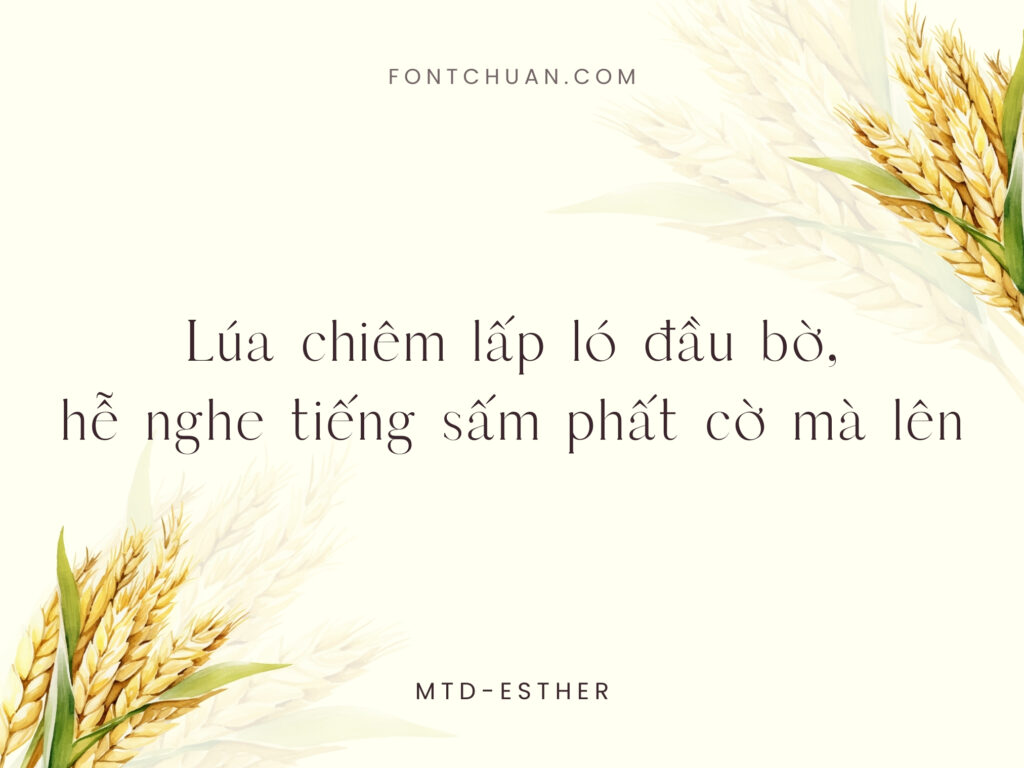
Font MTD Esther là một phông chữ serif thời trang, được thiết kế bởi SilverStag và phát hành trên FontBundles. Font đã được Việt hóa bởi Mộc Hạ, hỗ trợ tiếng Việt và hơn 90 ngôn ngữ khác, giúp mở rộng khả năng ứng dụng trong các thiết kế đa ngôn ngữ. Đây là một trong những phông chữ được cộng đồng thiết kế đánh giá cao và ứng dụng trong nhiều dự án sáng tạo, đáp ứng nhu cầu đa dạng của người dùng.
MTD Esther nổi bật với các đường nét thanh lịch, các ký tự được thiết kế tỉ mỉ với nhiều ligature và alternates, mang đến cảm giác sang trọng và hiện đại. Font rất phù hợp cho các thiết kế logo, tiêu đề tạp chí, thương hiệu thời trang, thiệp mời và các ấn phẩm đòi hỏi sự tinh tế và chuyên nghiệp. Các ngành nghề phù hợp bao gồm quảng cáo, giáo dục, công nghệ, thiệp cưới và ảnh cưới. Font này cũng lý tưởng cho các sự kiện như Tết, Giáng sinh, Valentine và các lễ hội khác.